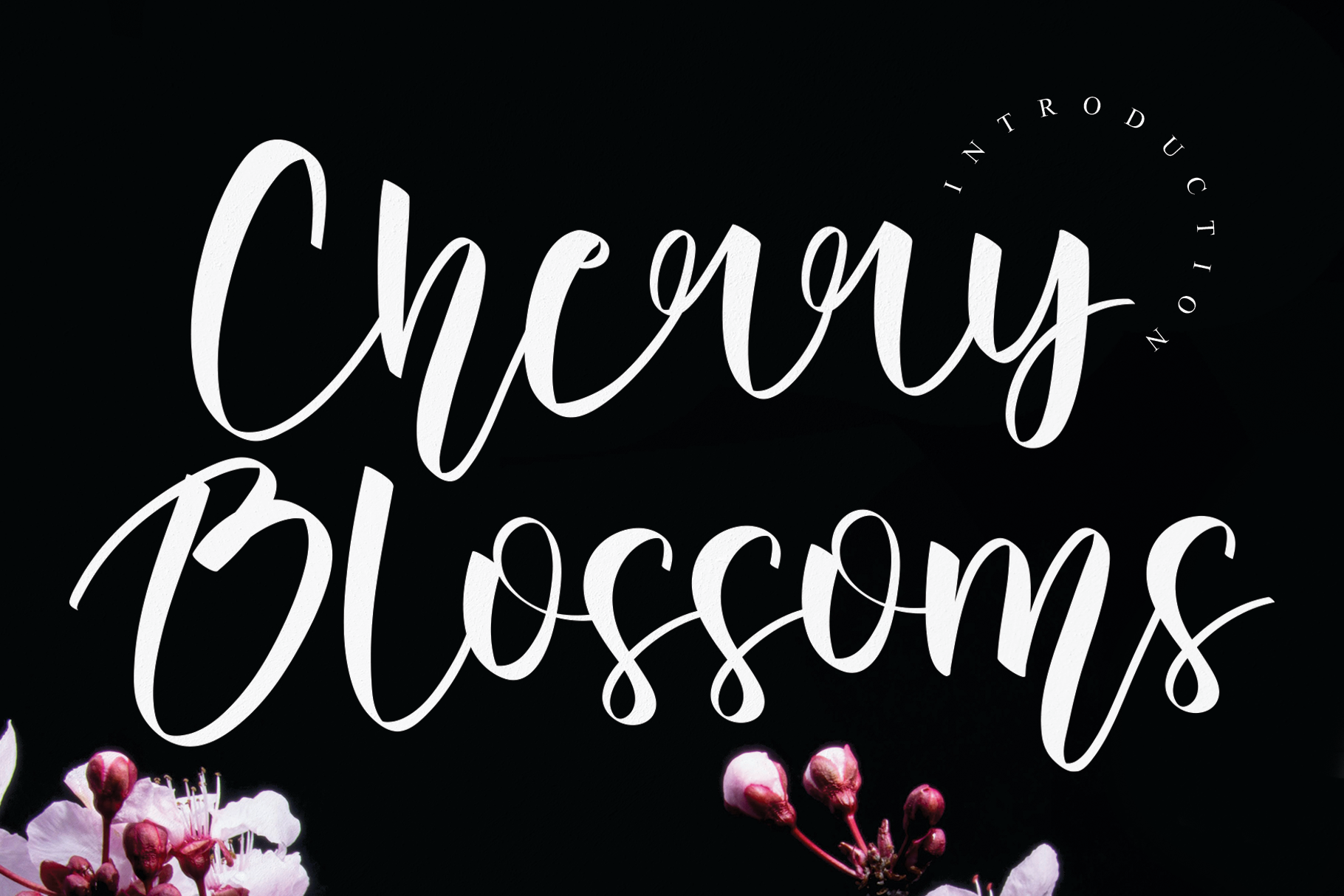
Cherry Blossoms Font – Fonte Grátis
Cherry Blossoms Font
A Cherry Blossoms Font é uma adição criativa para seus projetos digitais e impressos. Suavemente influenciada pela arte manual, esta fonte se destaca com sua elegância e delicadeza perfeita para estilos contemporâneos de design. Ideal para aplicar em cartões de convite de casamento, logotipos para publicações online ou até mesmo em gráficos de produtos, a Cherry Blossoms Font permite uma brilhante combinação entre modernidade e delicadeza, tornando-a perfeita para qualquer projeto que exija um toque único e encantador. Com seu design fluido e personalizado pelo designer creativeletter, a fonte oferece uma experiência visual incrível, seja você digitando em redes sociais ou trabalhando em projetos de comunicação gráfica. Seja qual for o projeto, a Cherry Blossoms Font é certamente um tesouro para os amantes da arte manual que buscam adicionar um toque delicado e original aos seus materiais impressos ou online.